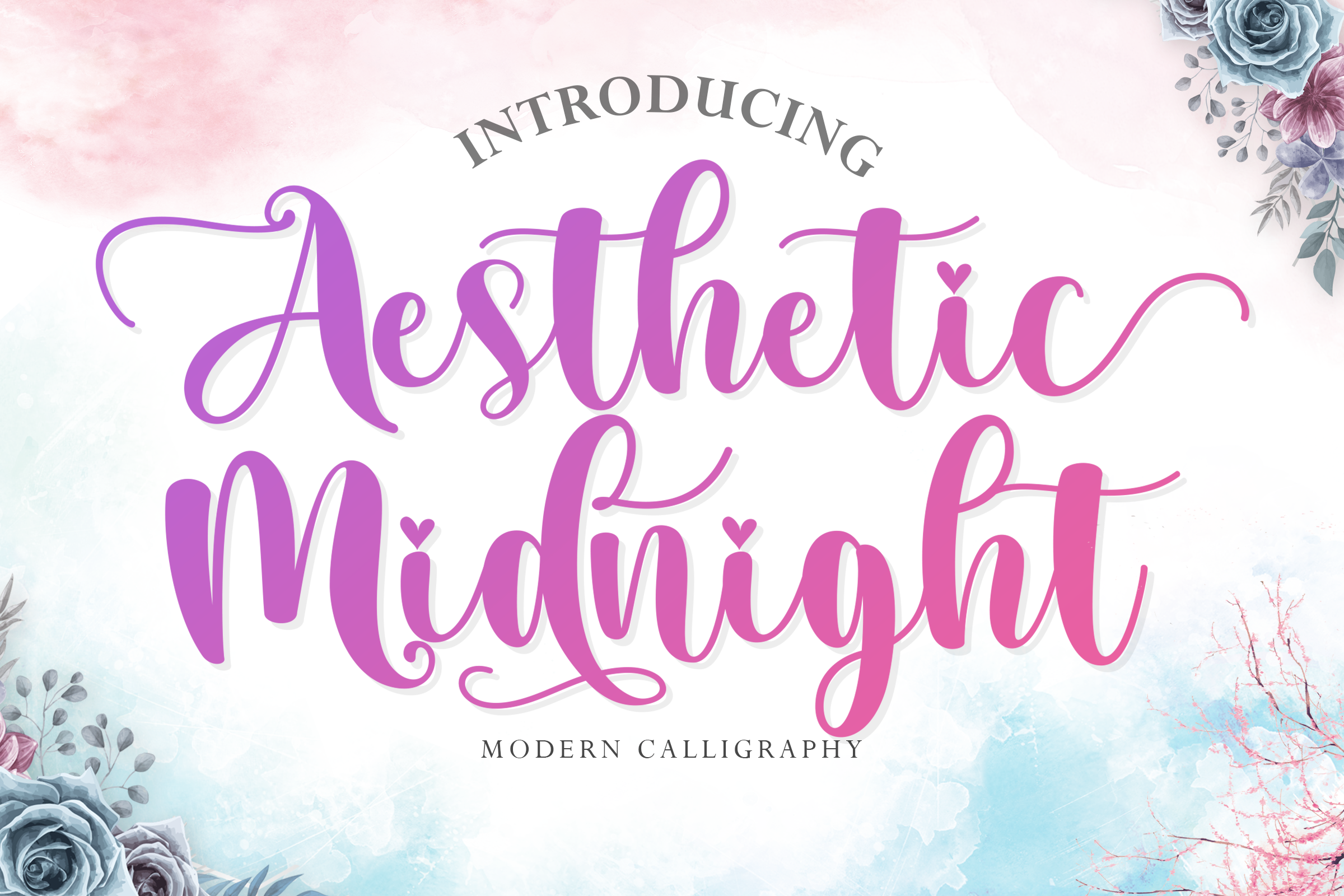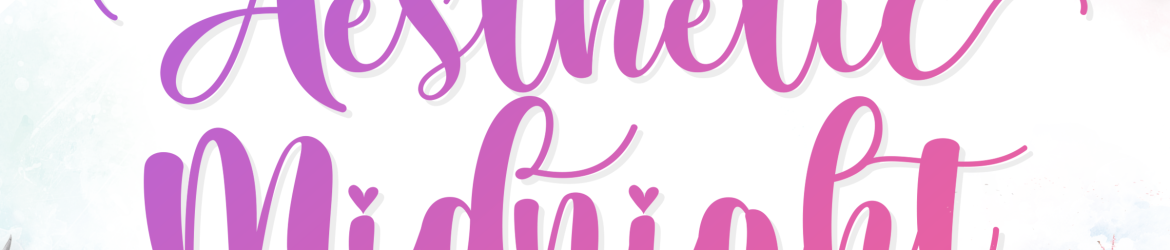
Aesthetic Midnight Font – Download Grátis
Bem-vindos ao mundo do design digital com a nossa nova adição à família Aesthetic Midnight Font. Projetada pela Elevatype Co., esta moderna tipografia calligráfica é perfeita para seus projetos visuais como banners, panfletos, convites e muito mais. Suave e elegante, ela não deixa nada a desejar em termos de qualidade e versatilidade. Ideal tanto para designers profissionais quanto aficionados por design, Aesthetic Midnight é um verdadeiro trampolim para criar ambientes criativos. Seja você um profissional em busca de uma fonte única que eleva seu trabalho ou alguém com o sonho de transformar suas ideias digitais em obras de arte perfeitas – esta font é definitivamente para você. Não espere, dê Aesthetic Midnight a chance e veja como ela pode transformar seus projetos design. Vamos desvendar os segredos do mundo da tipografia juntos!